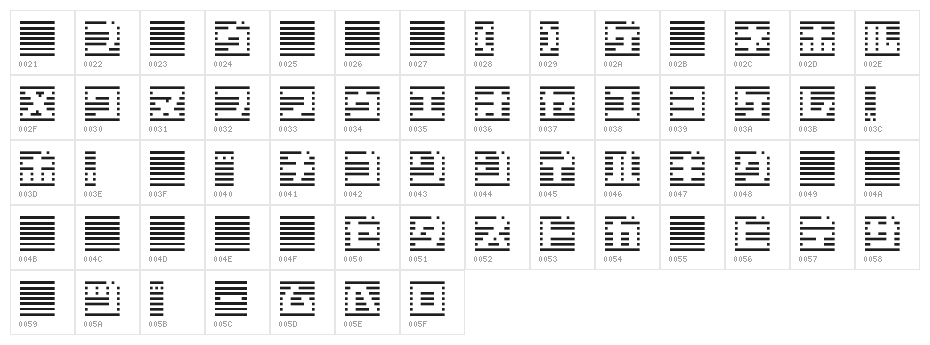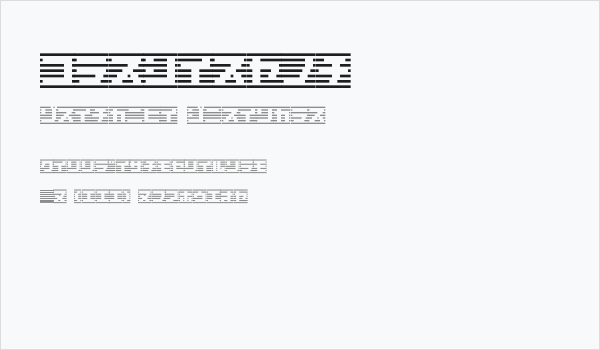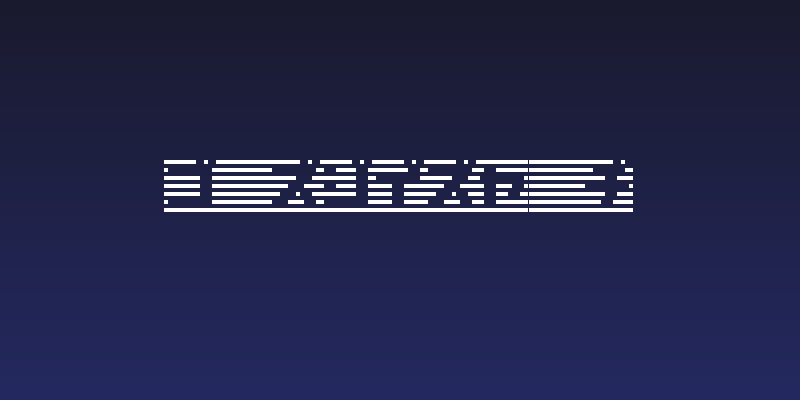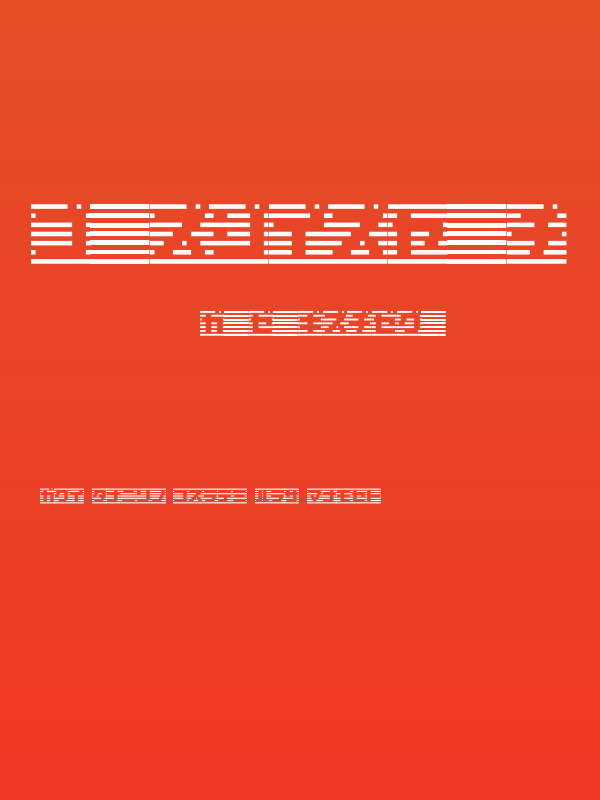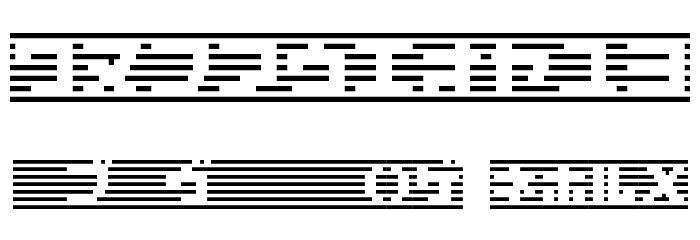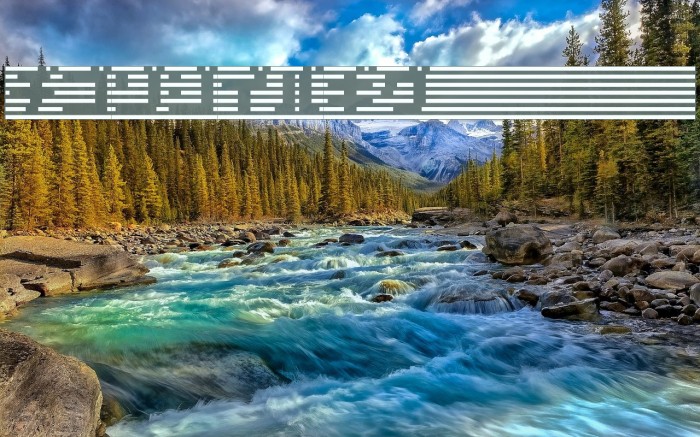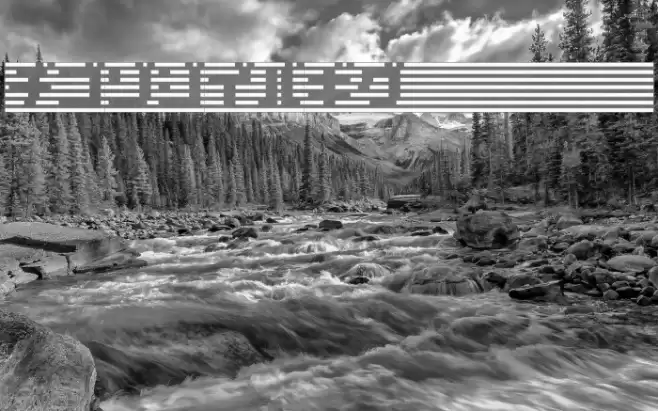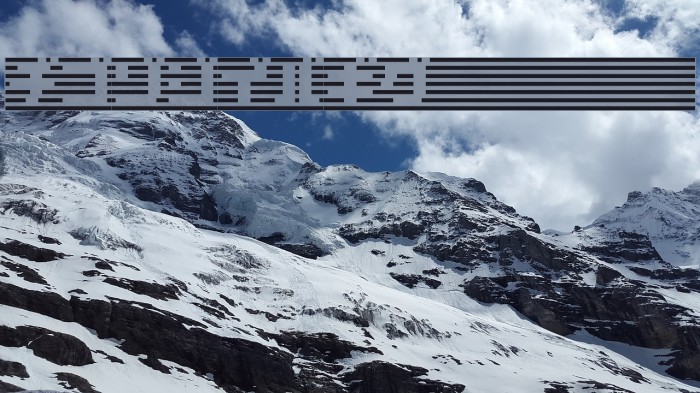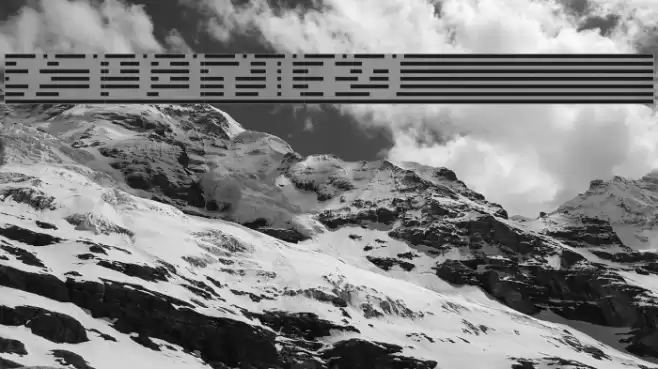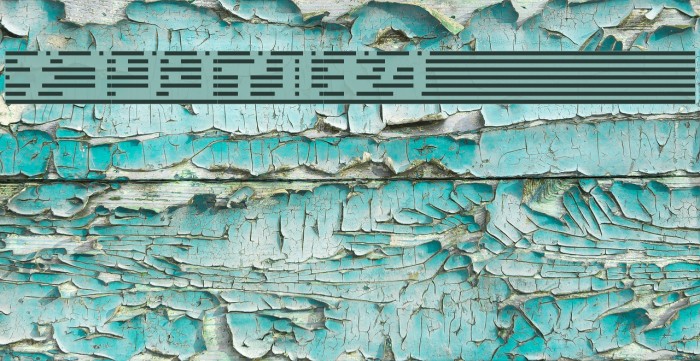
border7ka Font
| Projetos propostos | Ideal for tech-themed designs, futuristic branding, digital art projects, and innovative advertising campaigns. |